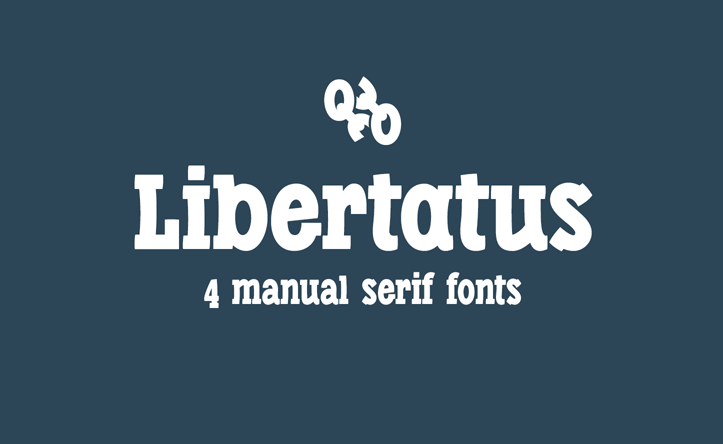
Libertatus Reg Font – Download Grátis
A fonte Libertatus Reg é uma opção divertida e contemporânea para designers que procuram um estilo Slab Serif com movimento único. Com serifs grossos e duas versões: Regular e Extra, esta fonte condensada oferece uma abordagem atraente ao design gráfico. As letras grandes incluem o símbolo Bitcoin, adicionalmente à sua combinação de ligaturas. A designer defharo concebeu estas linhas em um formato manual, mesmo que baseadas geométricamente. Através da modulação dos antebraços e terminais, criou uma sensação de movimento inusitado e alegre, resultando num estilo desconcertantemente moderno e divertido. Este é um excelente recurso para designers buscando algo diferente no seu próximo projeto gráfico.